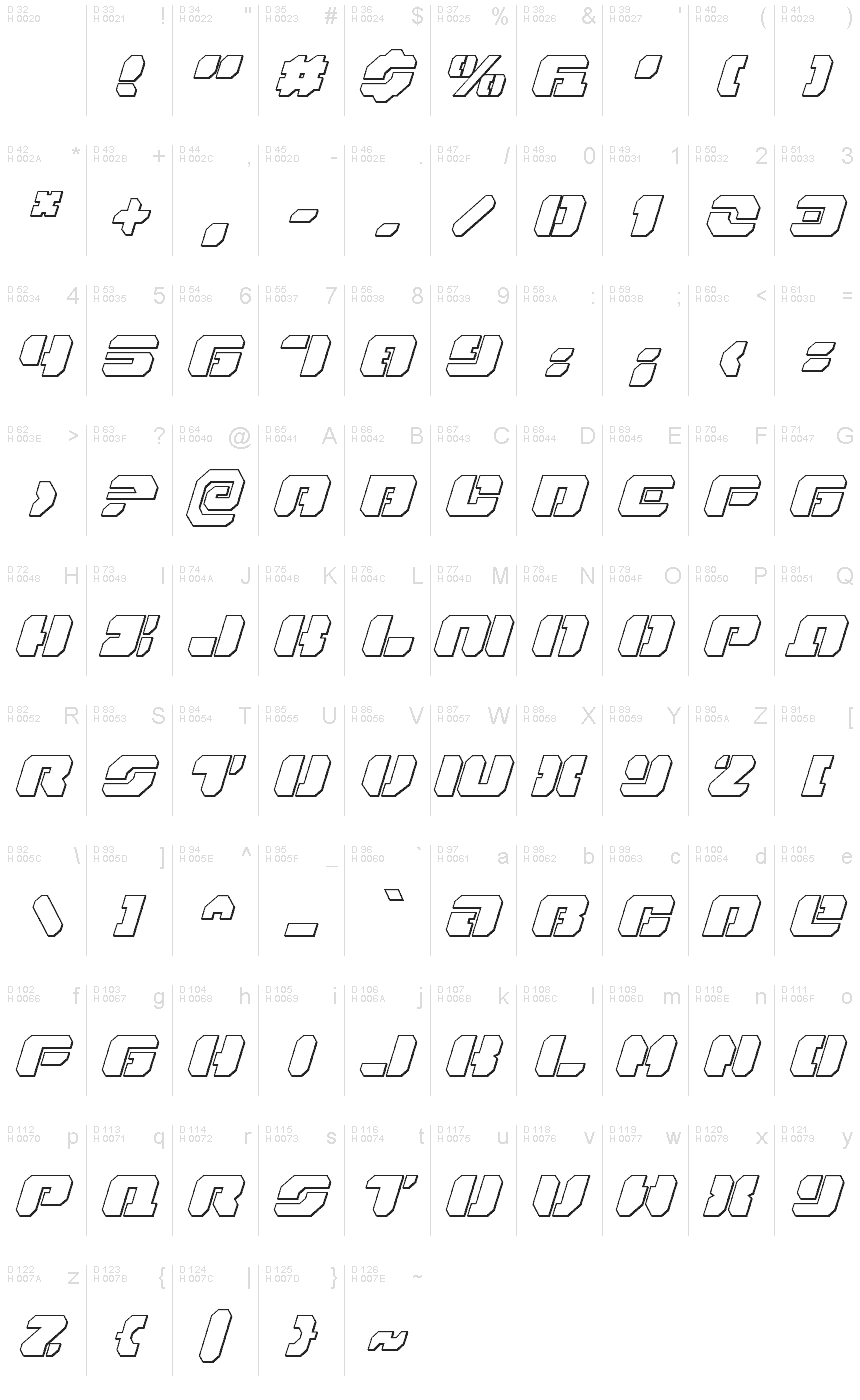
Dan Stargate Outline Italic di Iconian Fonts è un font display gratuito e futuristico con una forte impronta fantascientifica. Le lettere angolari e inclinate in avanti presentano angoli troncati, ampie forme geometriche e linee interne nette, richiamando alla mente le scritte su astronavi o la segnaletica tecnica.
Questo font gratuito si adatta perfettamente a loghi di giochi, poster tecnologici, branding per esports, copertine di album e titoli cinematografici. I contorni aperti e i tagli netti funzionano particolarmente bene per titoli brevi e testate, dove i caratteri hanno abbastanza spazio per mostrare il loro ritmo distintivo, simile a un circuito elettronico.